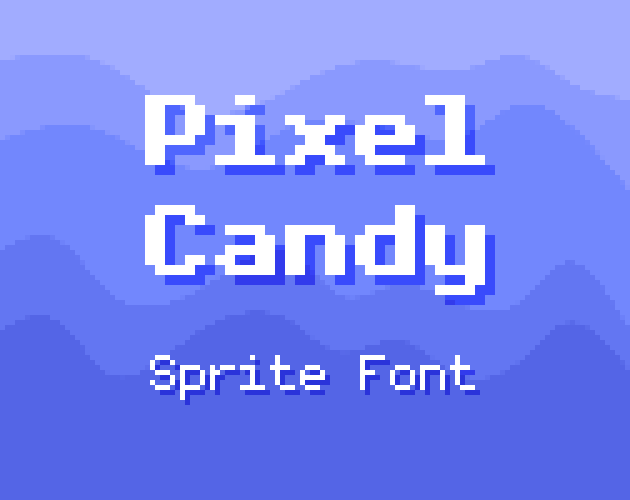
等宽的Pixel Candy像素糖果字体素材,Pixel Candy是一款等宽精灵字体。它用途非常广泛。
规格
• 字符集:ABCDEFGHIJKLMNOPQRSTUVWXYZÁÀÃÂÉÈÊÍÌÎÓÒÕÔÚÙÛÇabcdefghijklmnopqrstuvwxyzáàãâéèêíìîóòõôúùûç0123456789´`~^.,;:'”=+-*/\<>()[]{}?!@#$%&_|
• 常规字符大小:6×11
• 粗体字符大小:7×11
等宽的Pixel Candy像素糖果字体素材